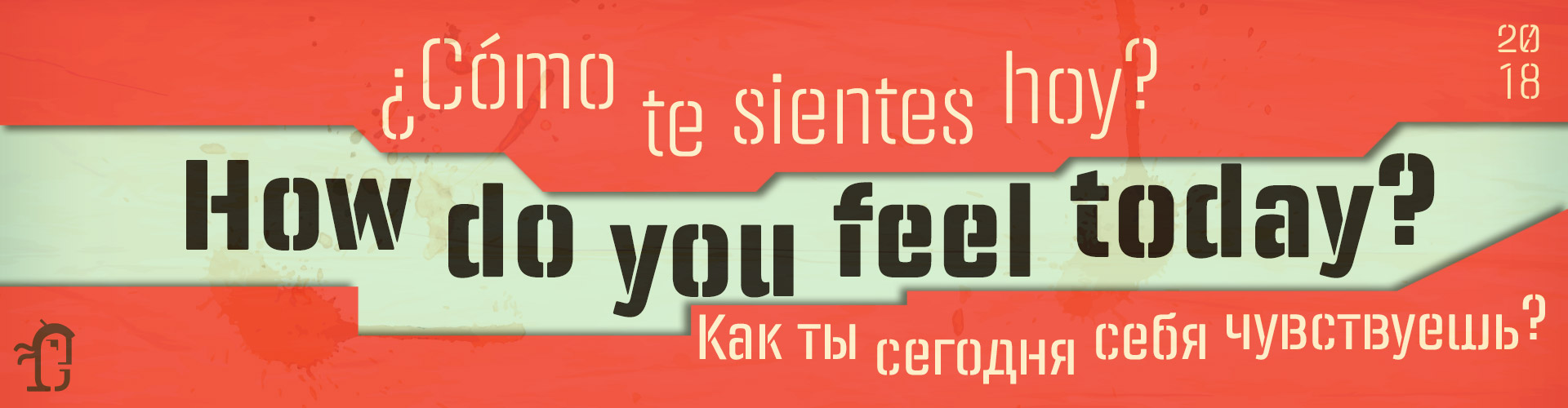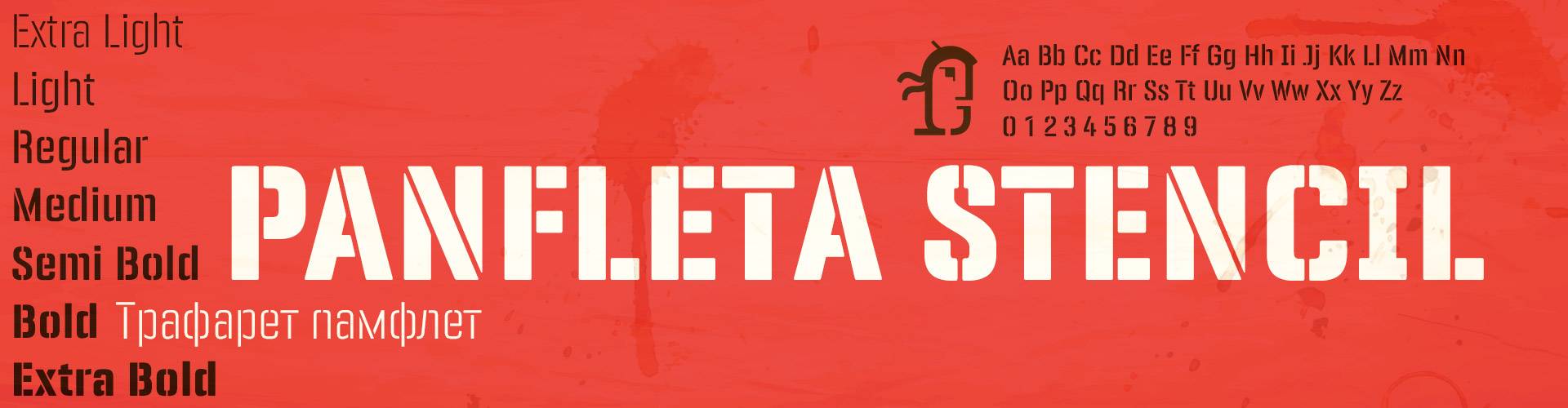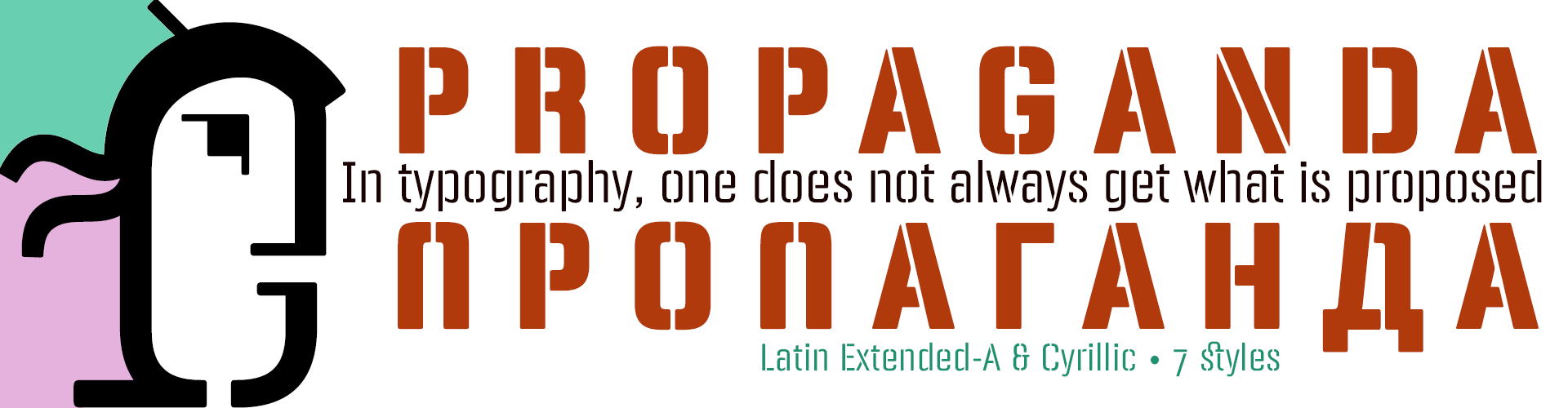
Estilo: Stencil, Sans Serif, Geometric, Condensed, Rounded, Industrial, Army.
Proporción: Extra Light, Light, Regular, Medium, Semi Bold, Bold & Extra Bold.
Glyphs: 681
Alternates: 34
Latin-Extended: Latín Básico, Europa Occidental, Central & Oriental & Cyrillic..
Autor: deFharo
Año de publicación: 2018.
Funciones OpenType: Additional languages, All Alternates, Alternate Annotation Forms, Capital Spacing, Denominators, Discretionary Ligatures, Extended Fractions, Historical Forms, Historical Ligatures, Inferiors, Kerning, Localized Forms, Numerators, Oldstyle Figures, Optical Size, Ordinals, Scientific Inferiors, Slashed Zero, Standard Ligatures, Subscript, Superior letters, Superiors, Superscript.
La inspiración para esta familia de fuentes viene de los viejos panfletos y carteles de propaganda política de principios y mediados del S.XX, en este caso el diseño estarcido añade connotaciones industriales, militares o comerciales siendo perfecta para el diseño de carteles, empaquetado o publicidad.
La tipografía se compone de 7 estilos, desde el más fino (Extra Light) al más grueso (Extra Bold) todas ellas especialmente diseñadas para la composición publicitaria y editorial, comportándose seriamente en textos de párrafo así como en grandes titulares. El soporte de idiomas de la tipografía está garantizado para todos los idiomas derivados del latín, además, incluye el alfabeto Cirílico, también funciones avanzadas OpenType disponiendo de 3 juegos de números diferentes, soporte completo para numerales, ordinales y fracciones, letras alternativas, ligaduras, diferentes símbolos monetarios internacionales incluido el Bitcoin y otras cripto monedas, etc. En el paquete completo de fuentes incluyo una versión en formato «Variable font» para usarlo con Adobe CC 2018.
La tipografía dispone de 681 glifos (Latin Extended-A & Cirílico) con funciones avanzadas OpenType, varios juegos de números, minúsculas alternativas y el símbolo del Bitcoin, con soporte para cualquier idioma europeo o centro europeo, incluye el alfabeto cirílico. Panfleta Stencil incluye funciones OpenType (Compatibles con InDesign, QuarkXpress, Photoshop e Illustrator.